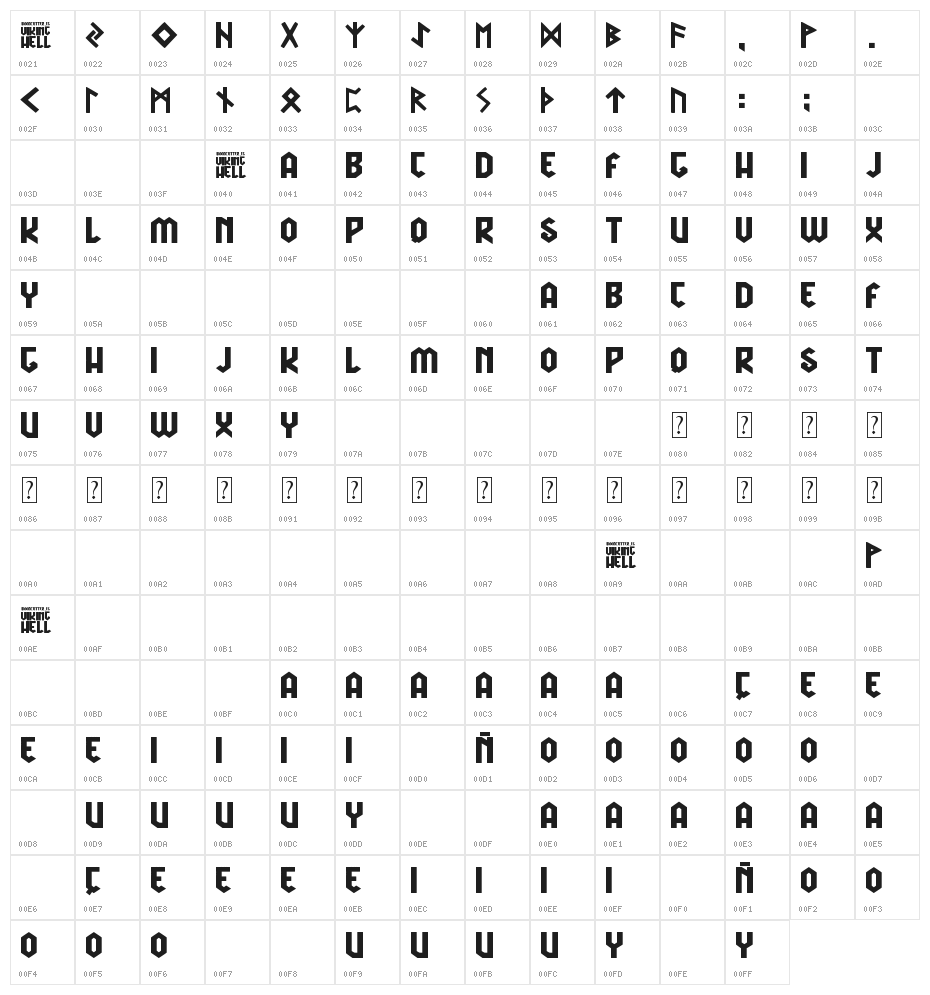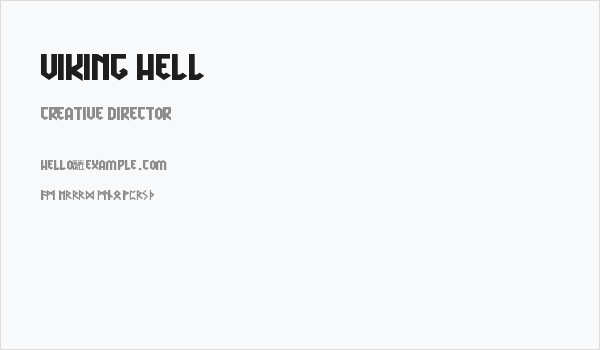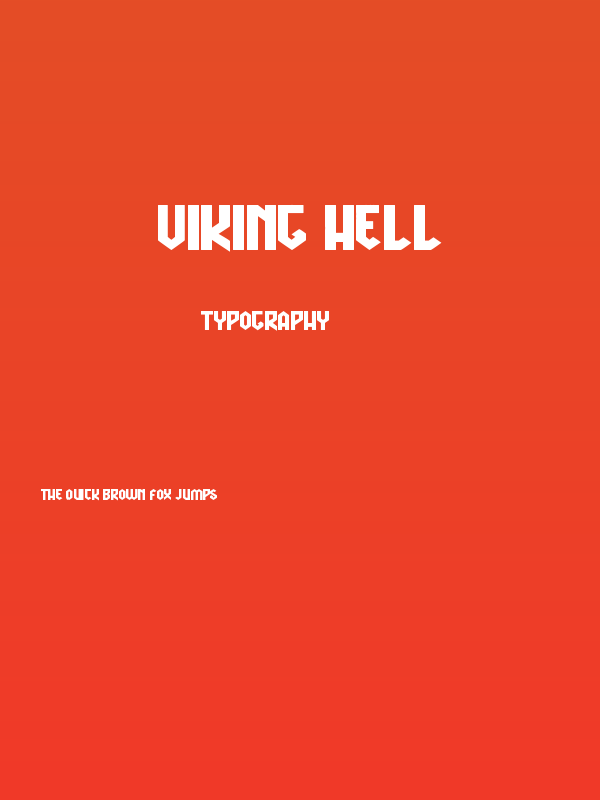
Viking Hell Font
| おすすめプロジェクト | Ideal for projects requiring a historical or mythical theme, such as fantasy book covers, video game titles, or themed event posters. |